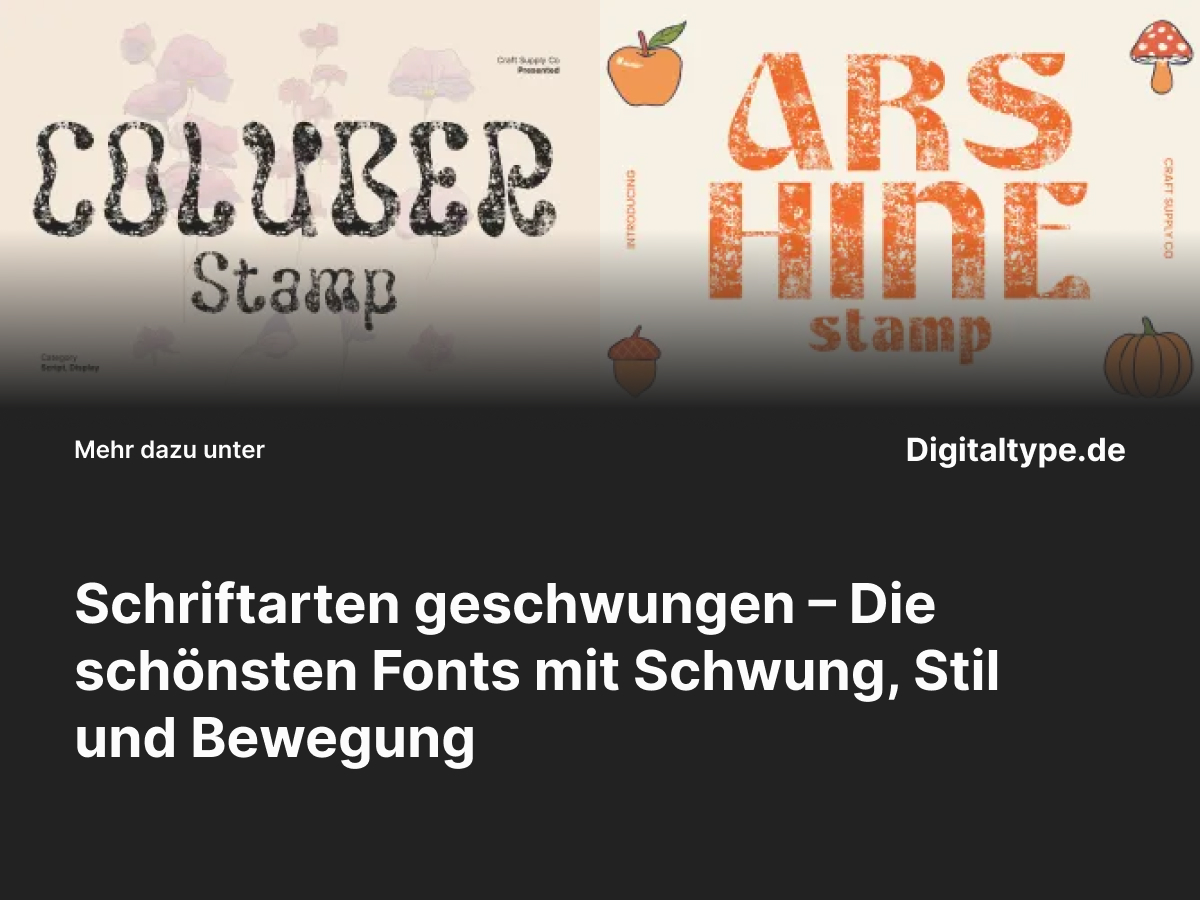
Schriftarten geschwungen – Die schönsten Fonts mit Schwung, Stil und Bewegung
Eine geschwungene Schriftart bringt Leben, Emotion und Eleganz in jedes Design. Ihre weichen Linien und harmonischen Kurven wirken verspielt, feminin oder luxuriös – je nach Stilrichtung. Ob für Einladungen, Logos oder kreative Zitate: Geschwungene Schriften ziehen sofort den Blick auf sich und verleihen deinem Design eine fließende, künstlerische Note. In diesem Artikel erfährst du, was geschwungene Schriftarten ausmacht, wann du sie einsetzen solltest und welche sieben stilvollen Alternativen du ausprobieren kannst.
Was sind geschwungene Schriftarten?
Geschwungene Schriftarten zeichnen sich durch sanfte, kurvige Linien und oft kalligrafische Elemente aus. Sie wirken dynamisch, elegant und fließend – wie von Hand geschrieben. Solche Fonts werden häufig in kreativen und emotionalen Kontexten verwendet, weil sie Bewegung und Ausdruck vermitteln.
Sie sind ideal, um einem Design Charakter zu verleihen. Ob luxuriös, romantisch oder modern – geschwungene Fonts können sich an jede Stimmung anpassen. Ihre Vielseitigkeit macht sie zu einem beliebten Werkzeug in der Typografie, besonders in Branding, Editorial- und Lifestyle-Projekten.
Wann du geschwungene Schriftarten verwenden solltest
• ✔️ Für Hochzeitseinladungen, Grußkarten und Zitate.
• ✔️ In Branding-Projekten, die Kreativität oder Eleganz ausdrücken sollen.
• ✔️ Für Logos oder Headline-Texte mit auffälligem Stil.
• ✔️ In Lifestyle-, Fashion- oder Beauty-Designs, die Bewegung und Weiblichkeit betonen.
Eine geschwungene Schriftart kann sowohl modern-minimalistisch als auch nostalgisch oder handgemacht wirken. Entscheidend ist, wie du sie kombinierst und einsetzt.
Die 7 schönsten geschwungenen Schriftarten
Hier findest du sieben sorgfältig ausgewählte Schriftalternativen, die geschwungene Formen und kreative Energie vereinen. Jede von ihnen bringt Bewegung und Ausdruck in dein Design – ideal für elegante, emotionale oder verspielte Projekte.
1. Coluber Stamp
Coluber Stamp ist eine künstlerisch gezeichnete geschwungene Schriftart mit Vintage-Charakter. Ihre organischen Linien und leicht unregelmäßigen Kurven verleihen ihr Authentizität und Charme. Ideal für Retro-Branding, Poster oder kreative Typografie-Layouts.
2. Arshine Stamp
Arshine Stamp kombiniert elegante Schwünge mit handgezeichneten Details. Die Schrift wirkt lebendig und individuell – perfekt für Projekte mit künstlerischem oder natürlichen Charakter, z. B. Verpackungsdesigns oder kreative Editorials.
3. CS Roast Whimsical Handwritten Font
CS Roast ist verspielt, weich und freundlich. Diese Schrift bringt Leichtigkeit und Humor in jedes Design. Ihre geschwungenen Buchstaben sind ideal für Lifestyle-Logos, Social-Media-Grafiken oder kreative Branding-Kampagnen mit positiver Ausstrahlung.
4. CS Piera Drawn Font
CS Piera kombiniert zarte Kurven mit handgezeichneter Textur. Sie wirkt künstlerisch, aber klar strukturiert – perfekt für Editorials, Illustrationen oder dekorative Headlines. Eine ideale Wahl für Designer, die Handarbeit und Eleganz verbinden möchten.
5. CS Lemon Drawn Font
CS Lemon ist frisch, kreativ und voller Bewegung. Ihre geschwungenen Buchstaben haben einen lockeren, natürlichen Rhythmus. Diese geschwungene Schriftart eignet sich hervorragend für kreative Marken, Food-Designs oder Lifestyle-Projekte.
6. Reifost Rounded Font
Reifost Rounded kombiniert moderne Geometrie mit weichen Rundungen. Sie ist ideal, wenn du geschwungene Formen suchst, aber eine klare, lesbare Struktur brauchst. Perfekt für moderne Marken, Start-ups oder digitale Designs mit sanftem Charakter.
7. CS Bourne Drawn Font
CS Bourne ist eine charmante, handgezeichnete Schrift mit subtilen Schwüngen. Ihre Linien wirken natürlich und künstlerisch – ideal für kreative Projekte, die Persönlichkeit und Originalität ausstrahlen sollen. Eine perfekte Mischung aus Vintage und Modernität.
Design-Tipps für geschwungene Schriftarten
• 1. Balance ist entscheidend: Kombiniere geschwungene Fonts mit schlichten Sans-Serif-Schriften, um Struktur zu schaffen.
• 2. Setze sie sparsam ein: Verwende Schwungschriften für Headlines oder Zitate, um ihre Wirkung zu verstärken.
• 3. Nutze weiche Farben: Pastelltöne, Gold oder Cremefarben harmonieren perfekt mit fließenden Schriftformen.
• 4. Achte auf Lesbarkeit: Vermeide zu enge Zeilenabstände und kleine Schriftgrößen bei sehr schwungvollen Fonts.
Fazit: Geschwungene Schriftarten für Eleganz und Ausdruck
Eine geschwungene Schriftart ist ein kraftvolles Gestaltungselement, das Emotion, Bewegung und Stil vereint. Sie verleiht jedem Projekt eine künstlerische, dynamische Note – ideal für Marken, die Eleganz, Kreativität oder Persönlichkeit betonen möchten.
Die oben vorgestellten Fonts bieten dir vielfältige Optionen – von handgezeichnet bis modern abgerundet. Probiere sie aus und finde heraus, welche geschwungene Schrift am besten zu deinem Designstil passt.